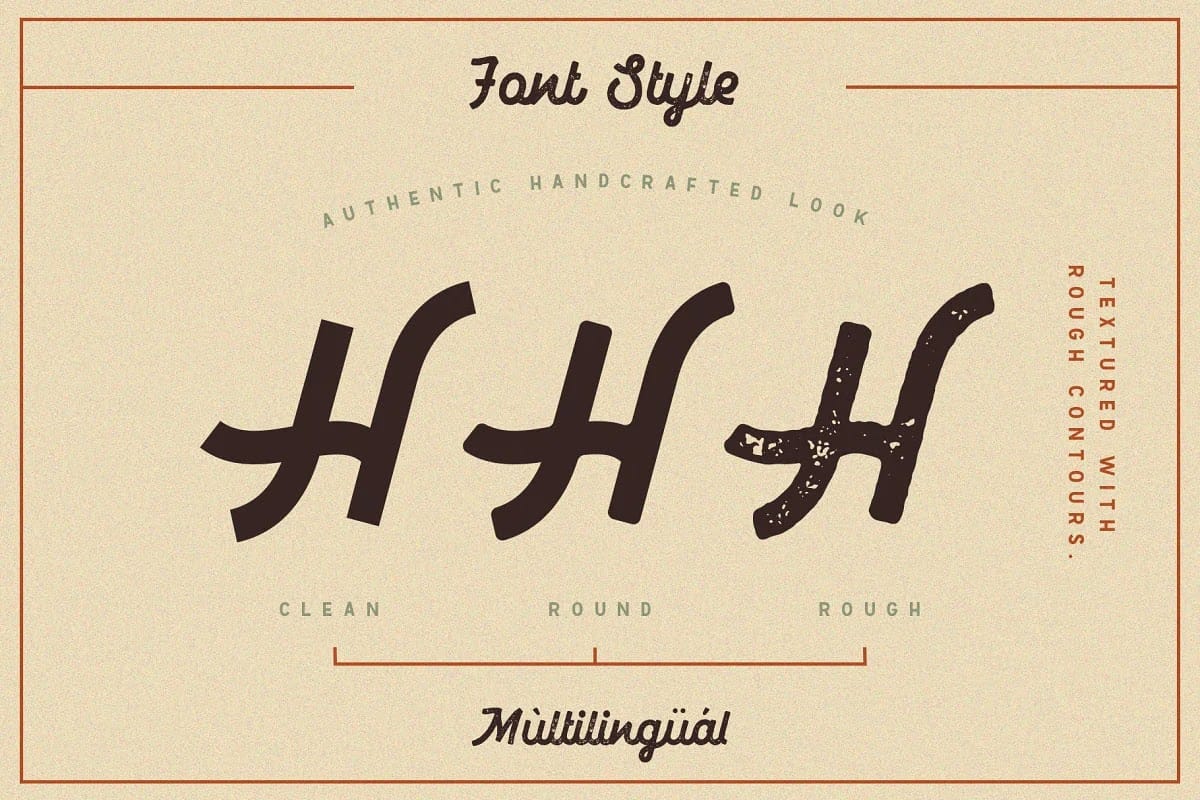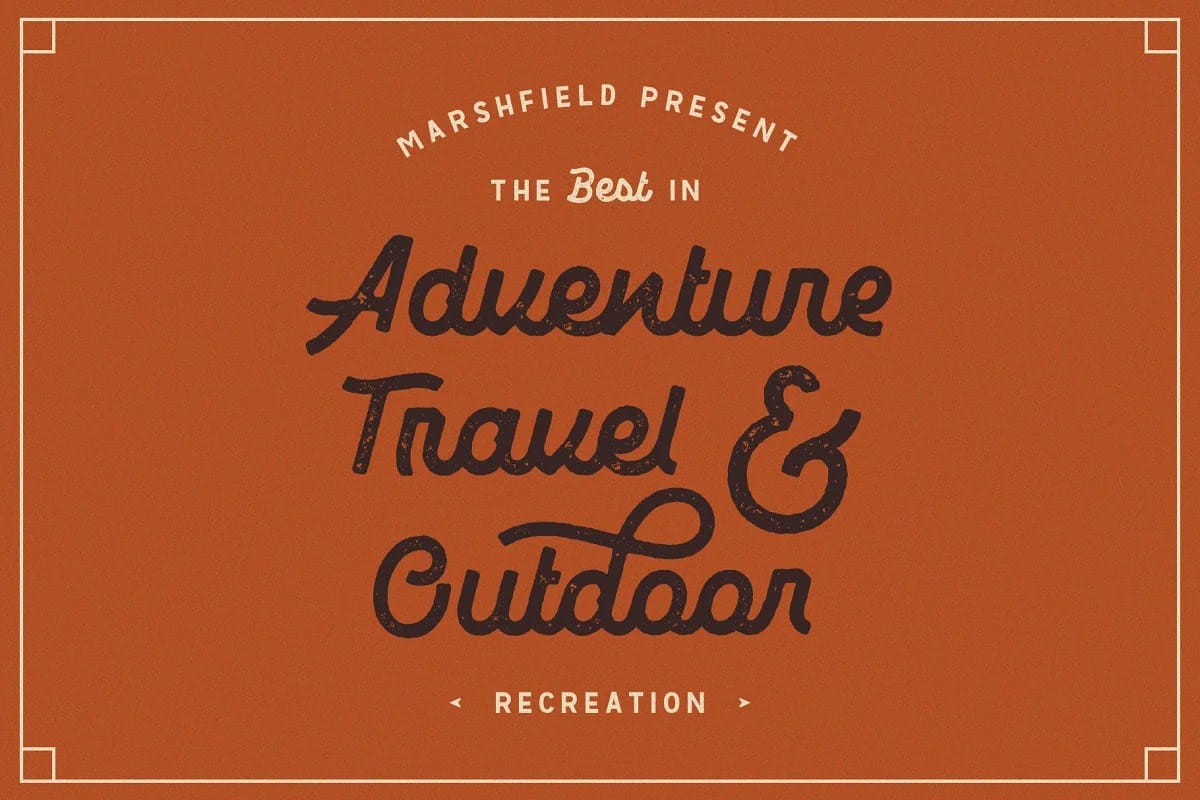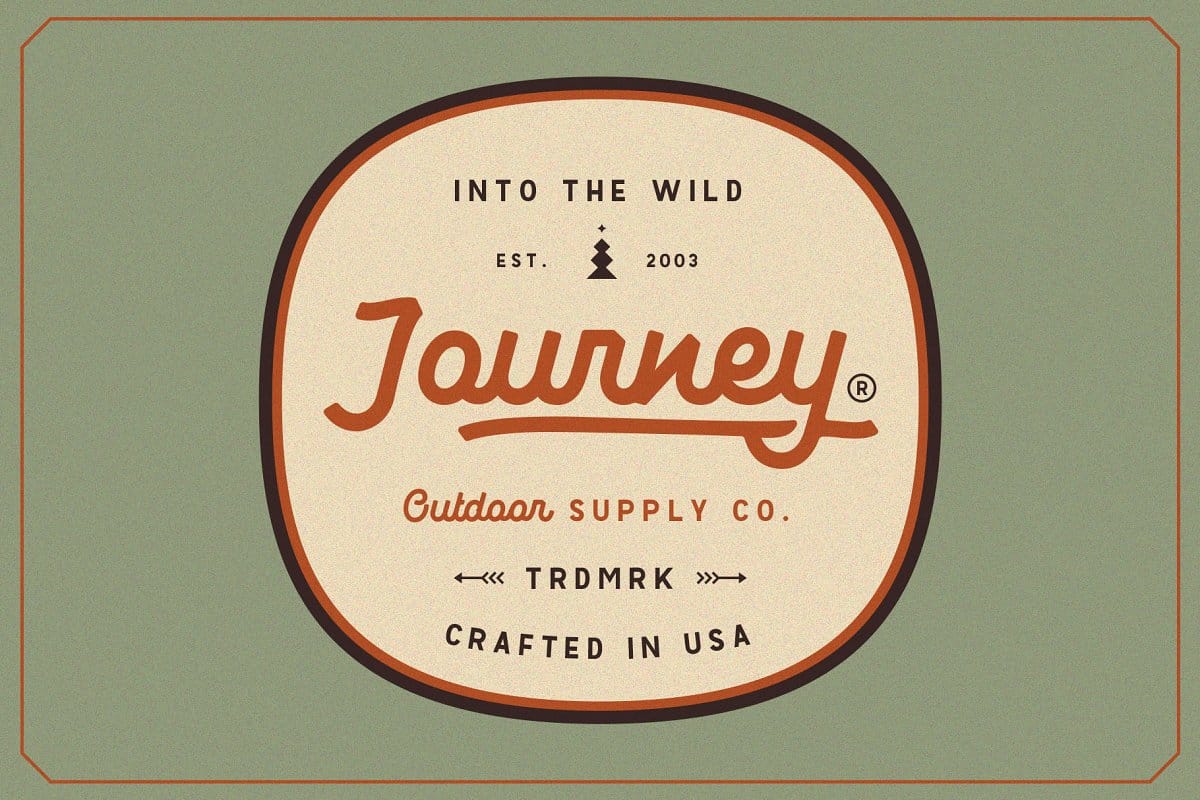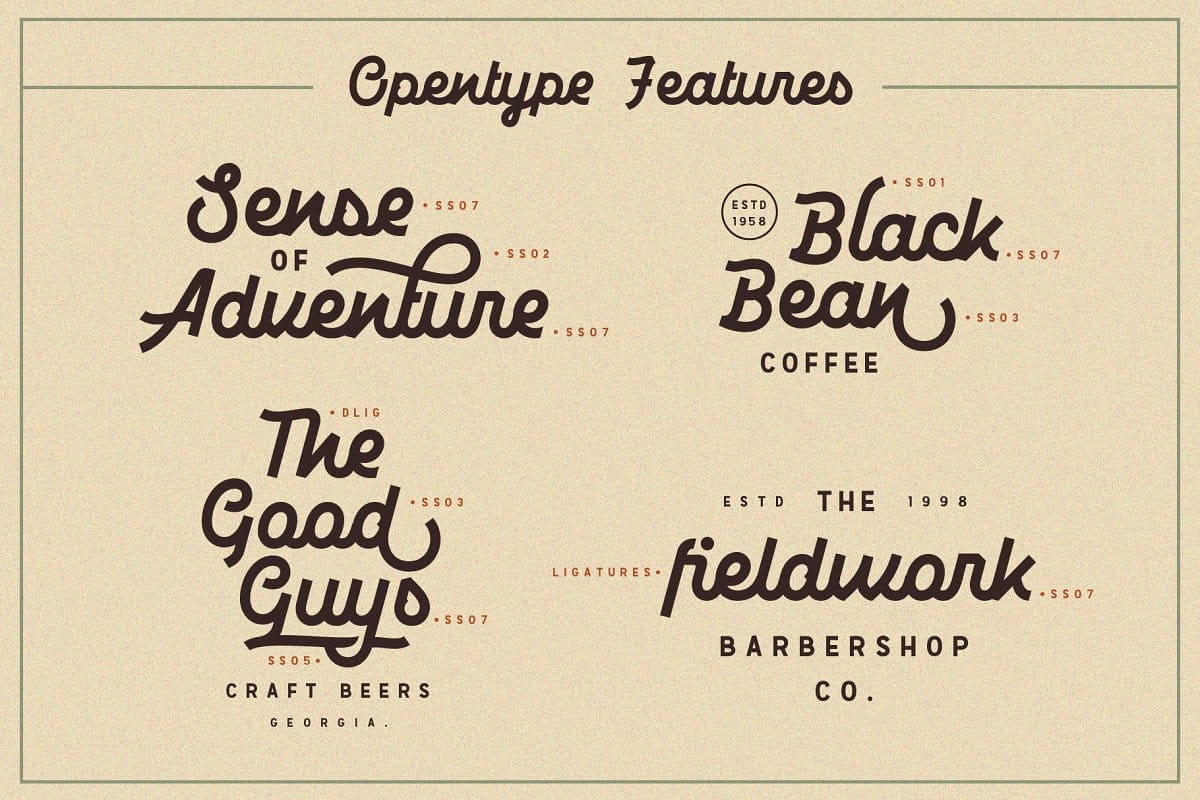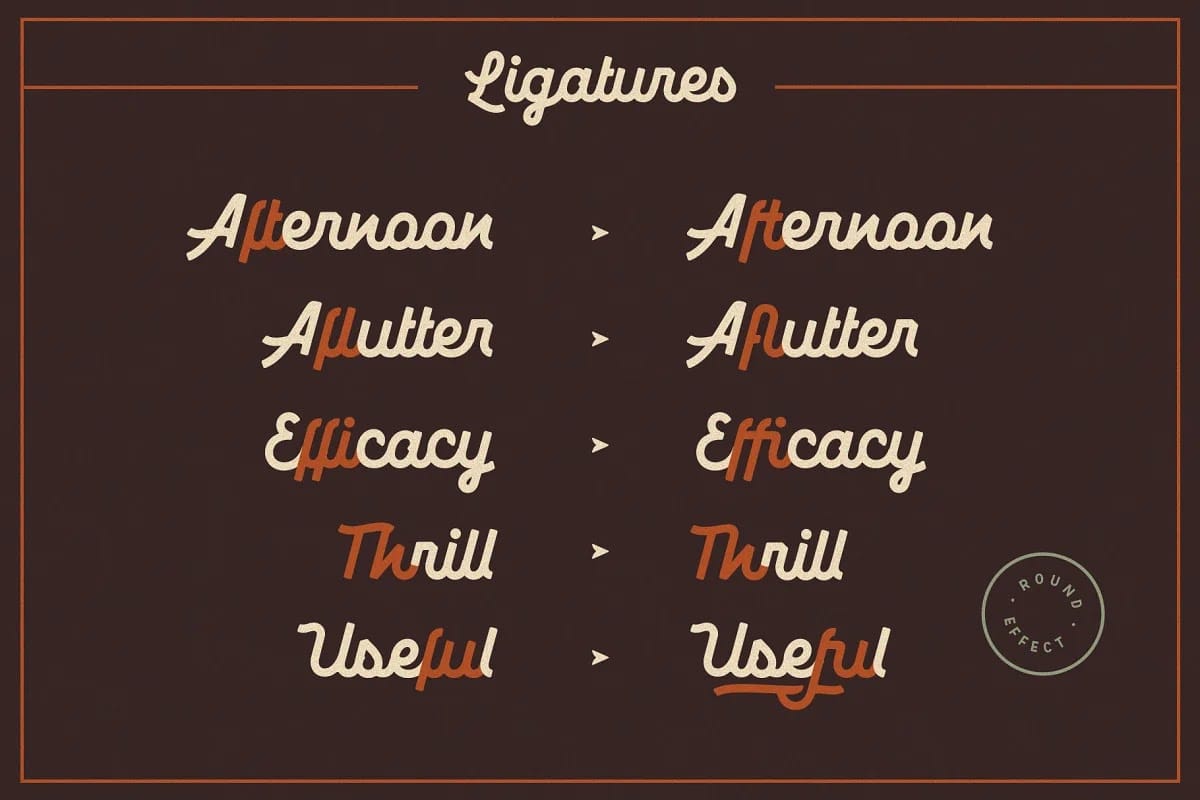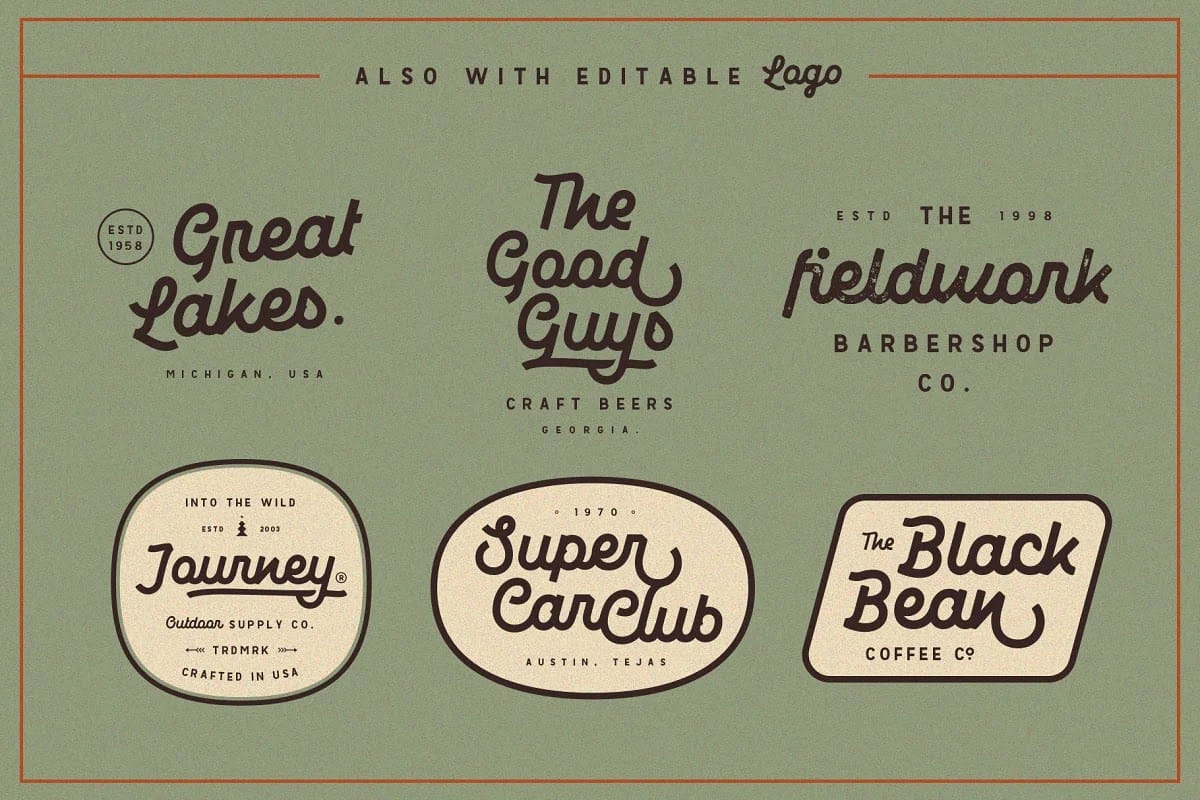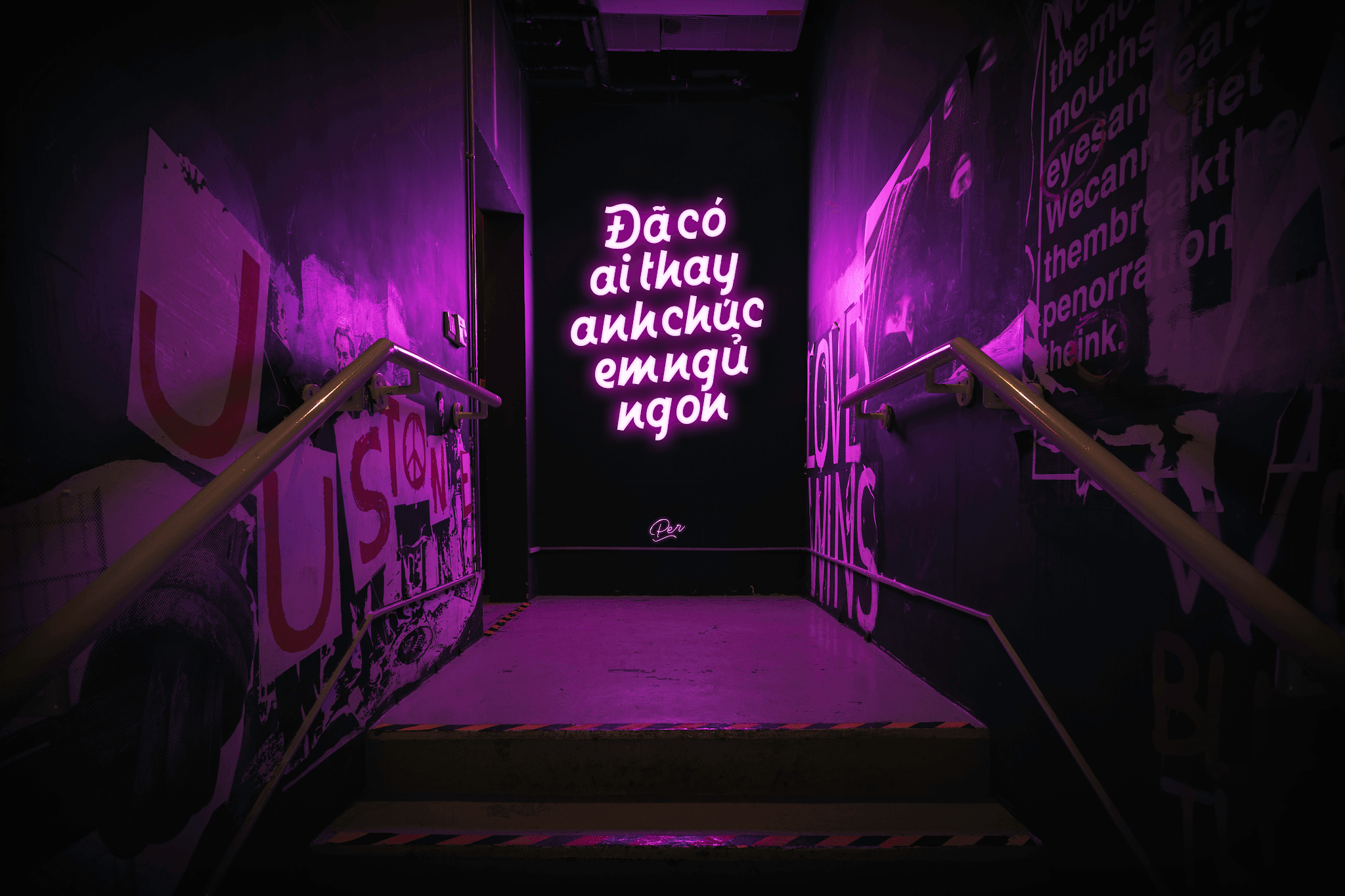
Font Marshfield Typeface Việt Hóa với sự cộng tác với Revolfe một nhà thiết kế với các dự án chữ viết tay.
Các tính năng Opentype có sẵn trên Marshfield như Ligatures, Stylistic Alternates (lên đến 6 Alternates), thay thế theo ngữ cảnh và thay thế đầu cuối.
Marshfield Đi kèm với 2 loại font chữ Script và Cursive. Trên mỗi loại font chữ có 3 kiểu khác nhau, Clean (góc nhọn), Round (Góc bo tròn), và Rough (Phiên bản thô) . Tổng cộng 6 font chữ để hoàn thiện phong cách thiết kế của bạn.